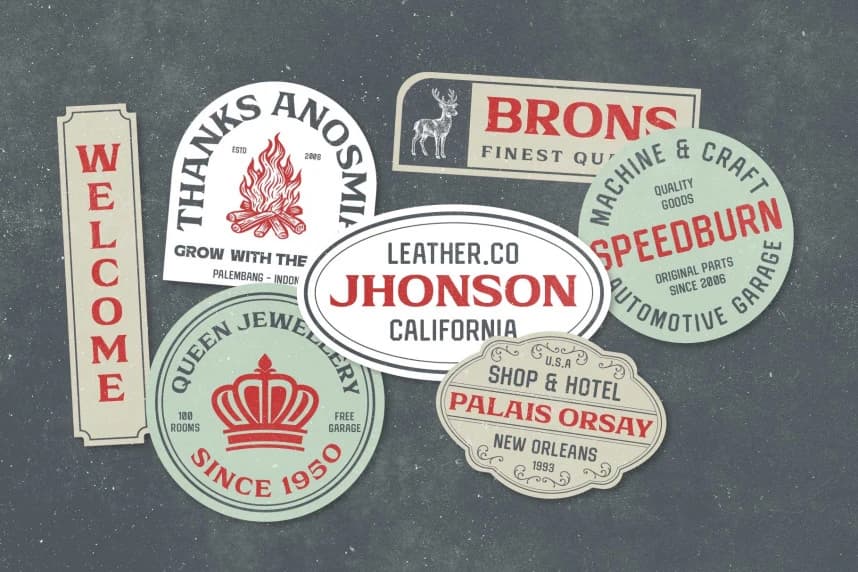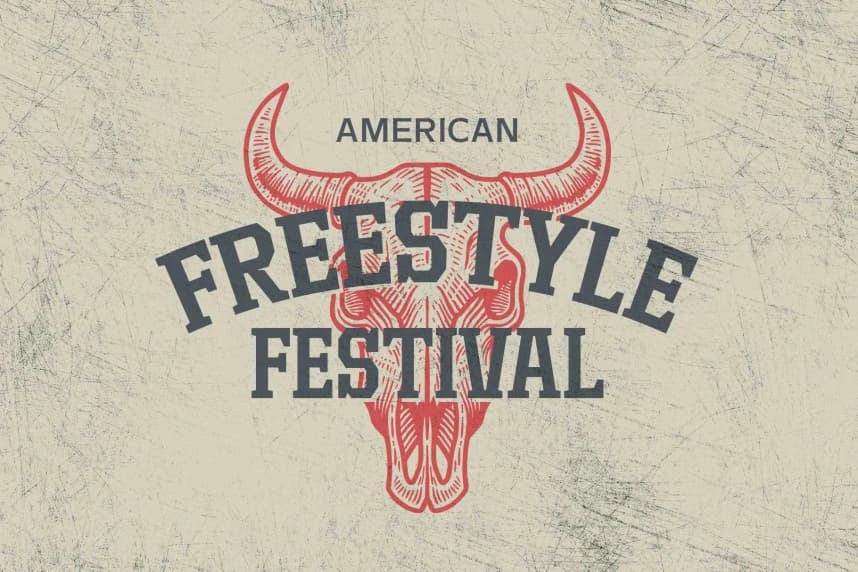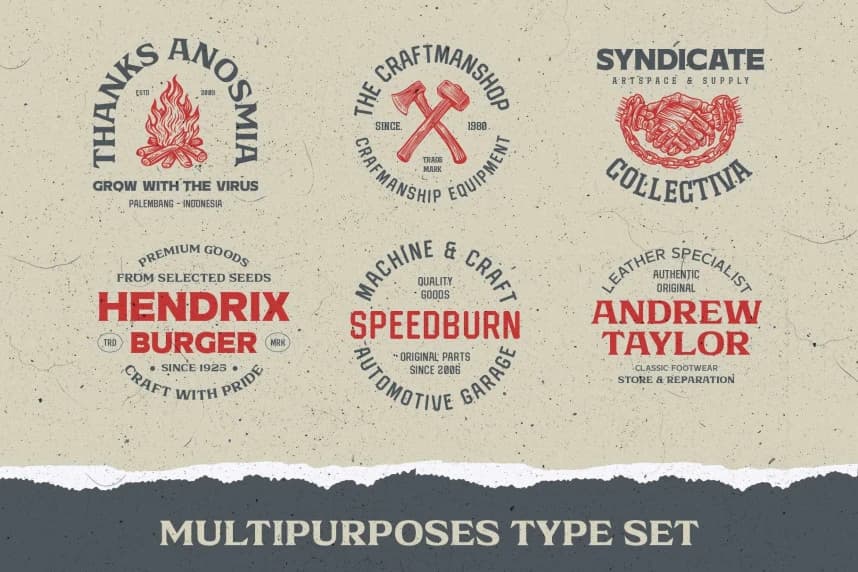
Survious Font – Vintage Yazı Tipi Seti. Eski etiketlerden ve eski okul illüstrasyonlardan ilham alan bu yazı tipi ailesi, klasik endüstriyel tarzı güçlü bir çok yönlülükle birleştirir. Sans Serif, Slab Serif, Wide Serif, Condensed Serif, Decorative ve Block stillerini içerir ve bu stiller birlikte s
Survious Font – Vintage Font Set. Eski etiketlerden ve eski okul illüstrasyonlarından ilham alan bu tip ailesi, klasik endüstriyel tarza güçlü bir çok yönlülük katıyor. İçerdiği Sans Serif, Slab Serif, Wide Serif, Condensed Serif, Decorative ve Block stilleri birlikte sorunsuz bir şekilde çalışır.